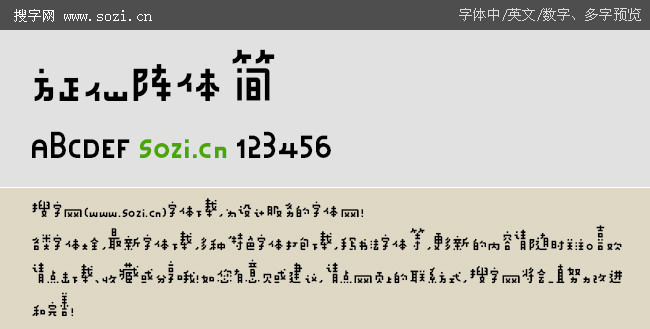
方正仙陣體-簡(jiǎn)
搜字網(wǎng)提供一款方正仙陣體中文藝術(shù)字體下載,仙陣體是基于方正基礎(chǔ)像素體的再創(chuàng)造,重設(shè)了筆畫結(jié)構(gòu),撇捺點(diǎn)進(jìn)行了1/4圓的圓弧設(shè)計(jì),折鉤部分設(shè)計(jì)成圓角,統(tǒng)一字體風(fēng)格的同時(shí)更添趣味性情感,較之更易識(shí)別、更具易讀性。適用范圍:字形適用于建筑、產(chǎn)品類設(shè)計(jì)的視覺設(shè)計(jì),以及時(shí)尚類品牌的廣告和包裝的設(shè)計(jì)。